50 najlepszych kolekcji czcionek szeryfowych
Opublikowany: 2022-04-28Szukasz najlepszych czcionek Serif , które pomogą Ci wyróżnić Twoją markę?
Czcionki szeryfowe, z niewielką uciążliwością, mogą być idealne do logo, projektów nadruków, par, czasopism, nagłówków, a nawet tekstów podstawowych. Trzeba wybrać taką czcionkę, która idealnie pasuje do jego marki i jest czytelna dla użytkowników.
Stworzyliśmy listę najlepszych czcionek szeryfowych , które pomogą Ci przeprojektować tekst lub materiał.
01. Times New Roman
Mówiąc o najlepszej czcionce, jak nie wspomnieć o klasycznym „Times New Roman”. Czcionka, która symbolizuje profesjonalne podejście, jest nadal jedną z najpopularniejszych czcionek. Zaprojektowany w 1932 roku, jest nadal używany podczas pisania listów biznesowych.
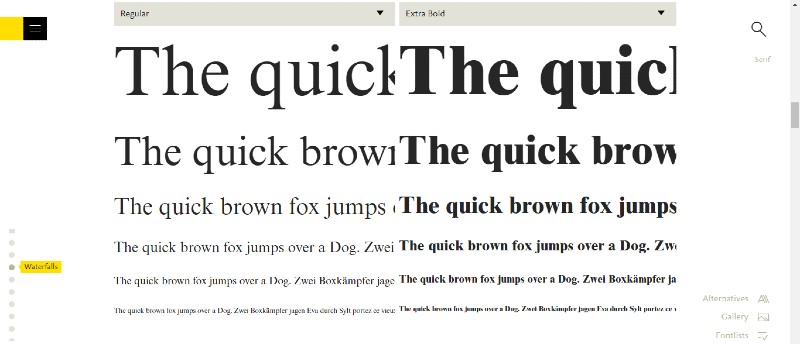
02. Adobe Caslon
Adobe Caslon to jedna z najprostszych czcionek, która osiągnęła legendarny status wśród typografów. Zawiera prawie wszystko, takie jak figury w starym stylu, alternatywy i kaligraficzne litery.
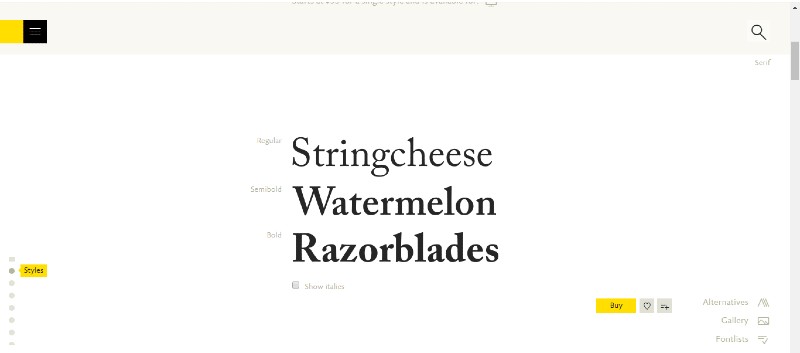
03. Palatyn
Jeśli chcesz mieć wiele opcji czcionek do wyboru, Palatino jest idealnym wyborem. Jego zakres czcionek obejmuje jasną, regularną, przechylaną, średnią, pogrubioną i imperialną. To nowoczesny klasyk, który sprawdza się zarówno w typografii tekstowej, jak i displayowej.
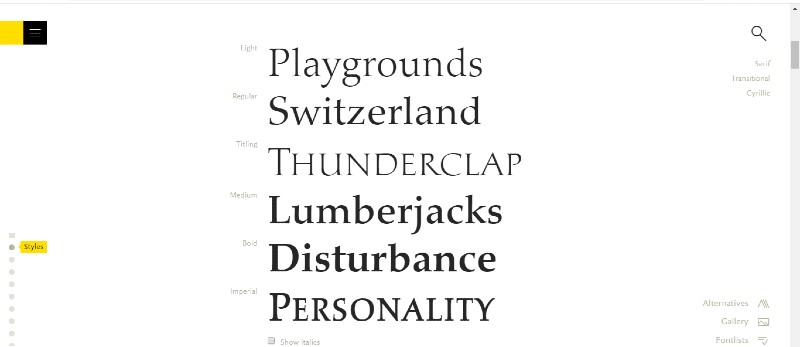
04. Tekst frachtu
Jedna z tych czcionek, które są tak miłe dla oczu, że będziesz pisać tym na zawsze. Możesz uzyskać tę czcionkę w kolorze jasnym, pogrubionym, średnim, półgrubym, książkowym, a nawet czarnym.
05. Sabona
Piękna czcionka Seif, idealna do użytku osobistego i komercyjnego. Zaprojektowany przez Jana Tschicholda i Akaki Razmadze, Sabon został stworzony, aby połączyć identyczne formy literowe dla maszyn monotypii i linotypu.
06. Roślina
Stworzony jako monotypia w 1913 roku Platin słynie z klasycznego i eleganckiego wrażenia. Zwarta budowa liter wraz z mocnym modelowaniem kresek sprawia, że Platin jest jedną z najlepszych czcionek Serif.
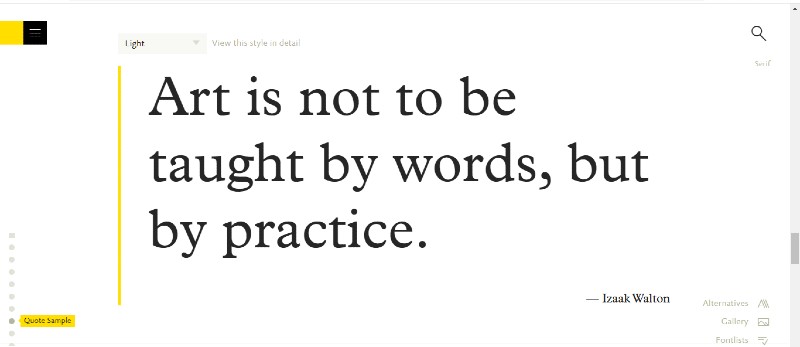
07. Gruzja
Zaprojektowany przez Matthew Cartera, Georgia ma przyjazny krój pisma, który można łatwo zrozumieć nawet przy niskiej rozdzielczości ekranu. Georgia to z pewnością jedna z najbardziej uroczych i stylowych czcionek Serif.
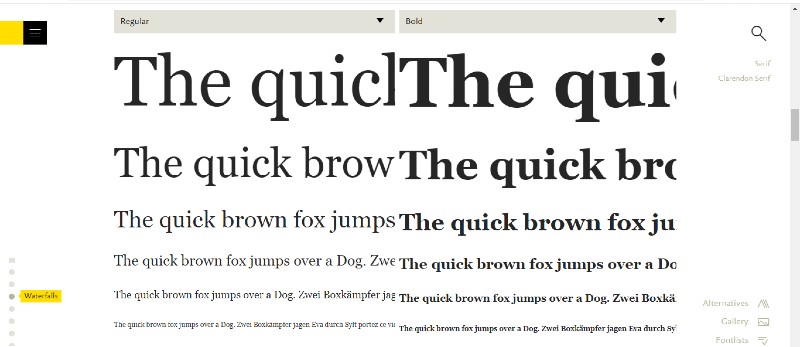
08. Cheltenham
Jeśli czujesz, że gdzieś widziałeś tę czcionkę, nie mylisz się. New York Times używa tej czcionki od wielu lat. Prosty, ale tradycyjny styl jest ulubieńcem fanów.
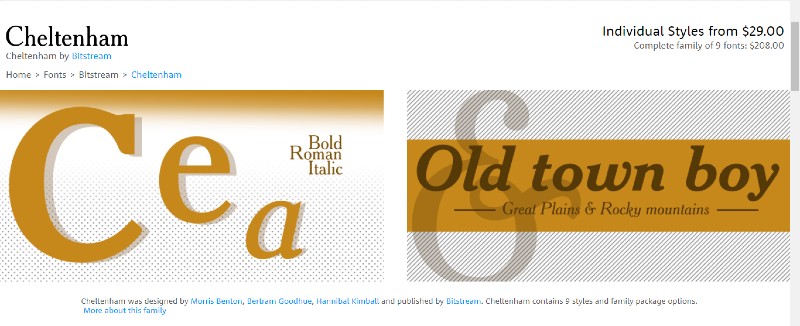
09. Czarniej
Nowa edycja w rodzinie czcionek Serif, Blacker, jest dostępna w ponad 10 grubościach czcionek. Szeryfowy wzór o wysokim kontraście, który może być idealny do użytku osobistego i komercyjnego. Zaprojektowali go Lorenzo Pancini i Andrea Tartarelli.
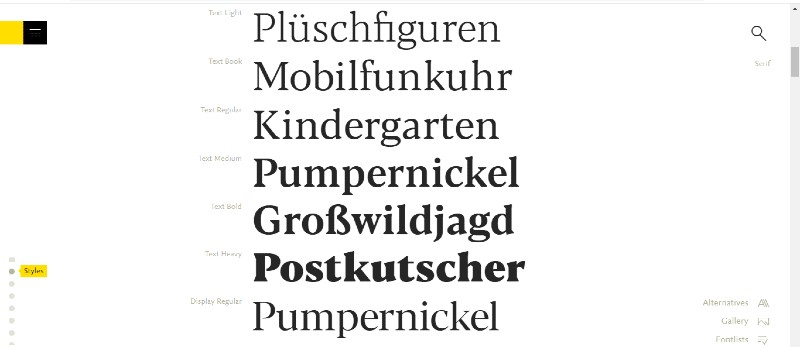
10. Bembo
Wagi czcionek wahają się od tytułu, półpogrubienia, pogrubienia do dodatkowego pogrubienia, istnieje wiele opcji do wyboru. Pełna wdzięku stabilność Bembo sprawia, że idealnie nadaje się do reklamy i pakowania produktów.
11. Begum
Luksusowe czapki typu flare szeryfowe sprawiają, że Begum jest jedną z najlepszych czcionek szeryfowych. Dzięki tej czcionce wprowadzenie do artykułów może zyskać nowy wymiar. Zaprojektowany przez Manushiego Parikha czerpie inspirację z późnego holenderskiego renesansu.
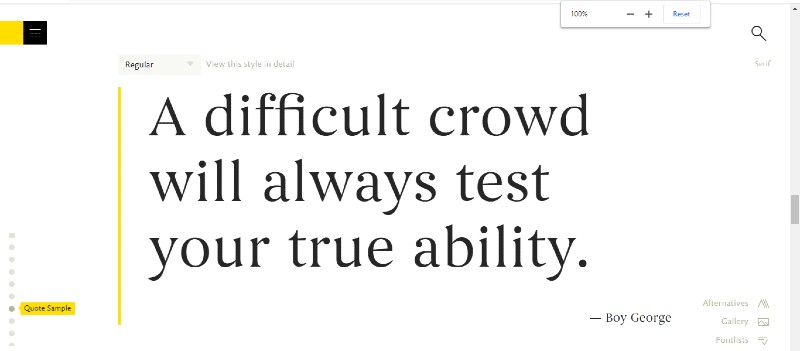
12. Baskerville
Dzięki ostrej i kontrastowej czcionce Baskerville'a materiały reklamowe będą należne. John Baskerville był człowiekiem, który zaprojektował ten piękny styl czcionki Serif.
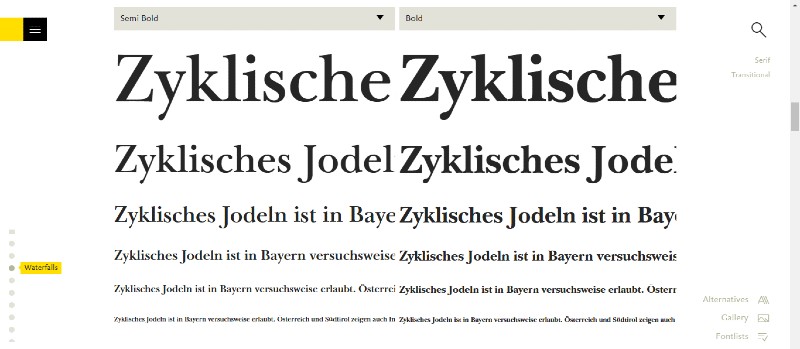
13. Czasy
Jako część nadrodziny Times, Times jest uważany za najczęściej używaną czcionkę szeryfową wszechczasów. Jest uważany za standard pod względem selekcji. Postacie Timesa są subtelnie skondensowane.
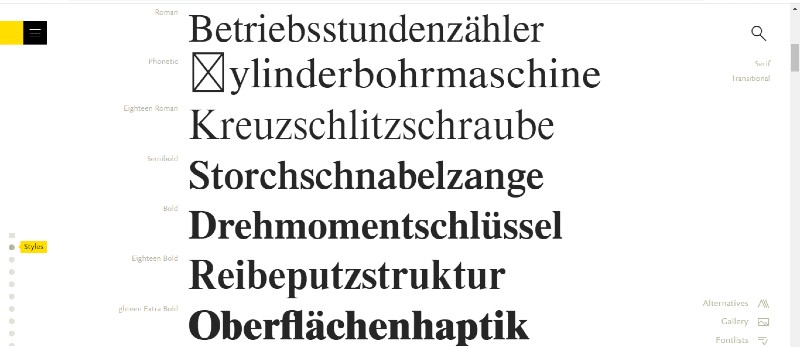
14. Rekoleta
Pięknie zaprojektowana czcionka, która nadaje się do logo, nagłówków i wizytówek, Recoleta jest nadal nowym członkiem rodziny czcionek Serif. Obecnie jest dostępny w 15 stylach.
15. Sługus
Zaprojektowany przez Roberta Slimbacha w 1992 roku, Minion zapewnia wyrafinowany dotyk potrzebny w stylu czcionki. Zainspirowany czcionkami późnego renesansu, minion ma ponad 60 stylów. Ta czcionka może być używana prawie wszędzie.
16. Arno
Dostępna w wielu grubościach czcionek, takich jak zwykła, pogrubiona, półgruba i kursywa, Arno to kolejna czcionka Serif zaprojektowana przez Roberta Slimbacha. Piękno tego tekstu polega na tym, że może sprawić, że każdy tekst będzie przyciągał wzrok.
17. Brak wyświetlacza
Jeśli szukasz czcionki Serif, która idealnie pasuje do dużego wyświetlacza nagłówka, Noe Display jest tutaj, aby rozwiązać ten problem. Jej wysoki kontrast z ciasnymi odstępami sprawia, że jest to jedna z 50 najlepszych czcionek Serif.
18. Tekst Tiempos
Czcionka szeryfowa, na którą duży wpływ ma wszech czasów klasyczna czcionka Times new roman, Tiempos Text, jest dostępna w czterech grubościach: zwykłym, średnim, pogrubionym i półgrubym. Został zaprojektowany przez Krisa Sowersby'ego.
50. FF Olsen
Zaprojektowany przez Mortena Rostgaarda Olsena w 2001 roku, FF Olsen został stworzony dla małych tekstów. Najlepszą cechą tego projektu jest to, że wygląda jak połączenie Sans i Serif, które może być doskonałą okazją dla projektantów do zaprojektowania logo.
Styl czcionki daje wrażenie Twojej osobowości lub Twojej marki. Dlatego ważne jest, aby wybrać odpowiednią czcionkę Serif.